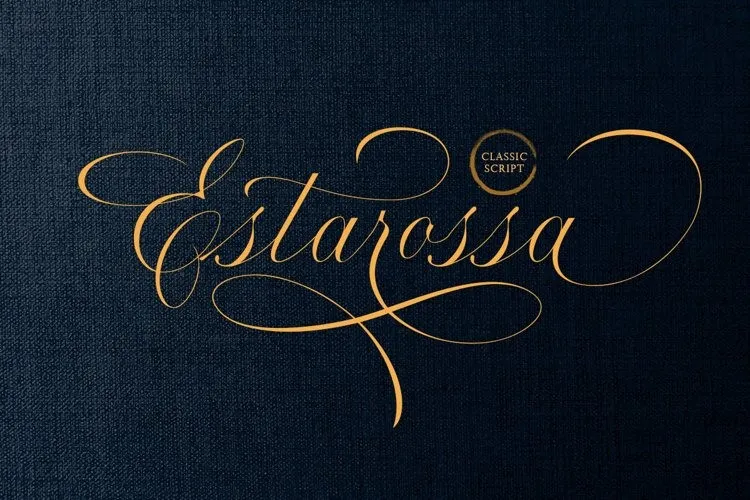
A ‘Estarossa Font’ é uma fonte script única que mistura a elegância dos velhos pressentimentos cromedistas com elementos contemporâneos. Ela possui um traço leve, quase dançante, resultando num charme sofisticado e refinado. Esta fonte tem muitas alternativas de estilo, ligaturas e swashes para que você possa explorá-la criativamente, utilizando suas características OpenType. Perfeita tanto para criar gráficos em logotipos como para outros formatos formais como convites, rótulos, logos, revistas, livros, cartas de aniversário ou casamento, embalagens, moda, maquiagem, papelaria e novelos, ou qualquer propósito de propaganda. A ‘Estarossa Font’ oferece um toque natural na escrita, tornando-a ideal para aqueles que desejam criar uma atmosfera agradável em seu próximo projeto visual.